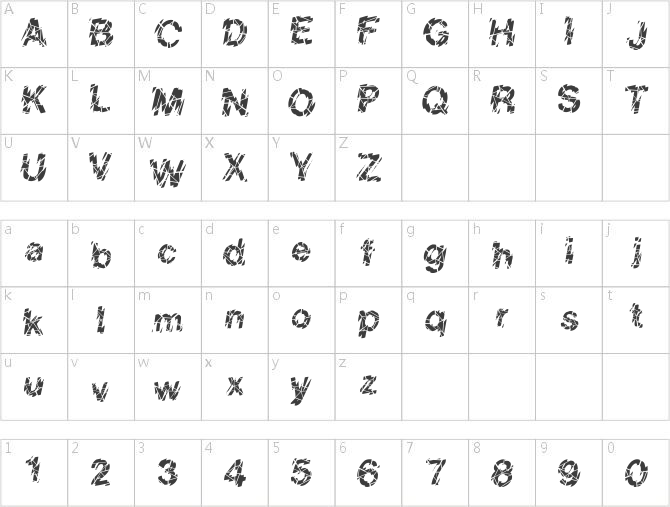
FZ UNIQUE 20 CRACKED 详情页
FZ UNIQUE 20 CRACKED
FZ UNIQUE 20 CRACKED介绍
FZ UNIQUE 20 CRACKED字体字库是一款让人赏心悦目、百看不厌的英文字体,适合各类广告和产品包装设计应用,字体大小0.11MB,格式为ttf字体,上传用户是FaYu,作者/版权方为未知